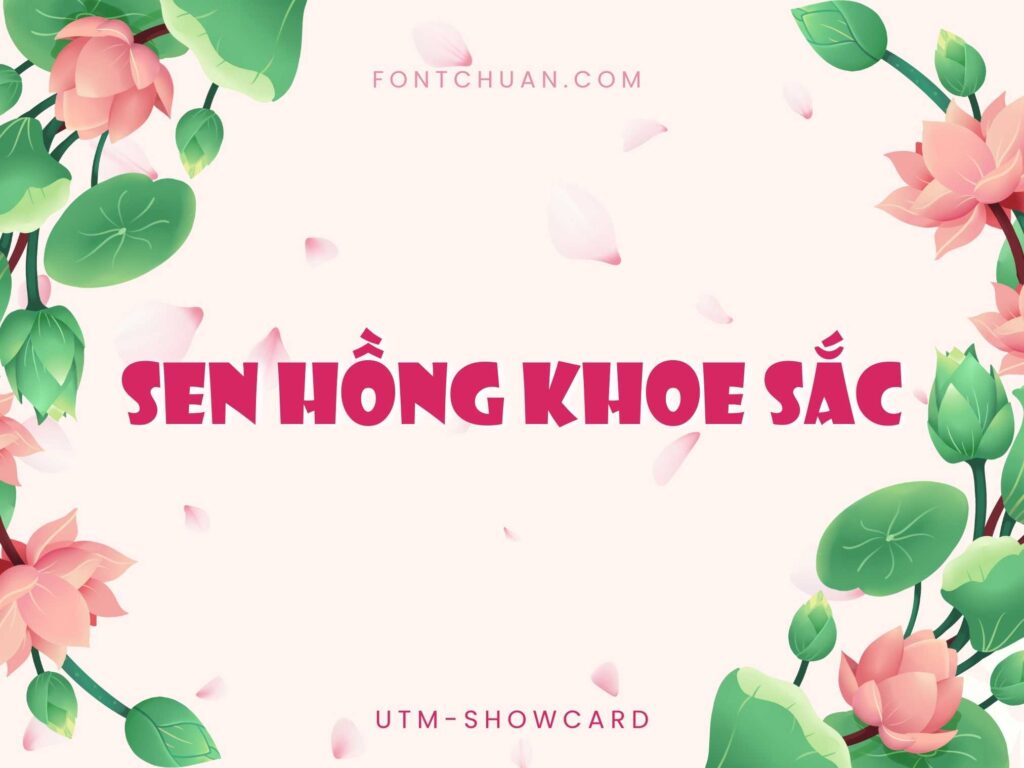
UTM Showcard là một font chữ trang trí nổi bật, thuộc bộ sưu tập font UTM. Với thiết kế đậm nét và phong cách độc đáo, font này mang lại cảm giác mạnh mẽ và thu hút cho các thiết kế. Đặc điểm nổi bật của UTM Showcard là sự kết hợp giữa tính nghệ thuật và sự rõ ràng, phù hợp cho các dự án như poster, tiêu đề, banner và các ấn phẩm quảng cáo khác. Font này đã được Việt hóa bởi Thiên Minh, đảm bảo hỗ trợ đầy đủ các dấu và ký tự tiếng Việt, mang lại trải nghiệm sử dụng hoàn chỉnh cho người dùng. Ngoài tiếng Việt, UTM Showcard còn hỗ trợ nhiều ngôn ngữ khác, mở rộng khả năng ứng dụng trong các thiết kế quốc tế. Thành viên của Font Chuẩn đã sưu tầm và giới thiệu UTM Showcard đến cộng đồng thiết kế, giúp họ có thêm lựa chọn cho các dự án sáng tạo.
Với sự kết hợp giữa tính thẩm mỹ và khả năng ứng dụng cao, font này phù hợp cho các thiết kế poster, tiêu đề, banner và các ấn phẩm quảng cáo khác.